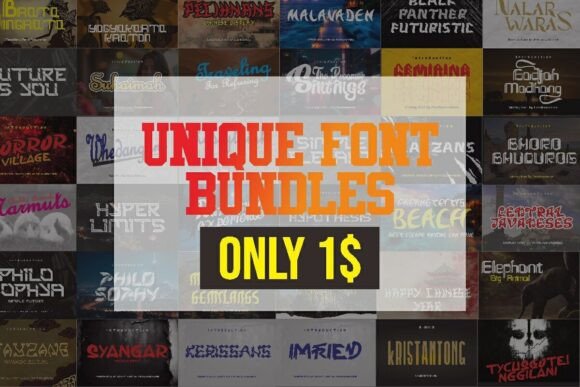
Unique Font Bundle
หากคุณกำลังมองหาเนื้อหาคุณภาพสูงเช่น Unique Font Bundle แพ็คเกจพรีเมียมนี้เป็นตัวเลือกที่ยอดเยี่ยมสำหรับโปรเจ็กต์สร้างสรรค์ของคุณ
ไม่ว่าคุณจะสร้างผลิตภัณฑ์ POD (Print on Demand) คำเชิญงานแต่งงาน หรือกราฟิกโซเชียลมีเดีย Unique Font Bundle ก็เหมาะสมอย่างยิ่ง